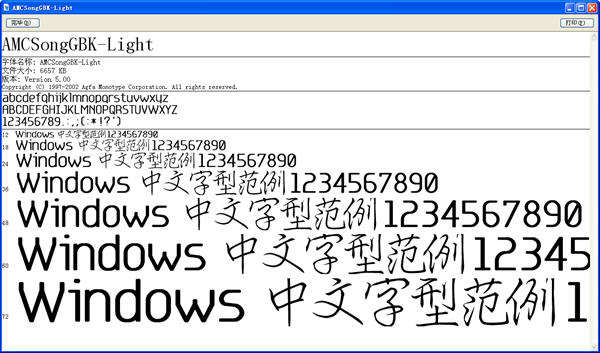
龐中華行書字體是一款非常好用的行書字體,小編為大家?guī)?lái)的是ttf版本,安裝即可使用,字體非常之硬朗,同時(shí)字體沒有那么工整,又帶著一絲活潑的味道,歡迎喜愛的朋友到綠色資源網(wǎng)下載體驗(yàn)!
龐中華,重慶市人,祖籍四川達(dá)州。著名書法家、教育家和詩(shī)人。當(dāng)代中國(guó)硬筆書法事業(yè)的奠基人?,F(xiàn)任文化部中國(guó)硬筆書法協(xié)會(huì)主席,龐中華書法藝術(shù)中心院長(zhǎng)以及國(guó)內(nèi)外一百多所大學(xué)、院校及文化團(tuán)體的顧問、名譽(yù)教授、名譽(yù)校長(zhǎng)等職務(wù)。除書法外,還長(zhǎng)于詩(shī)歌、散文、音樂、演講等藝術(shù)。自一九八零年以來(lái),有三百多種字帖和專著出版發(fā)行,其圖書總印數(shù)累計(jì)達(dá)一億三千萬(wàn)冊(cè)。 中央電視臺(tái)、中國(guó)教育電視臺(tái)多次邀請(qǐng)他主辦;硬筆書法講座;系列節(jié)目,受眾數(shù)以億計(jì)。海內(nèi)外數(shù)家報(bào)刊、電視臺(tái)、電臺(tái)熱情介紹了龐中華的書法藝術(shù)活動(dòng),推動(dòng)7國(guó)內(nèi)外硬筆書法的熱潮。他創(chuàng)辦的龐中華硬筆書法中心及學(xué)院,迄今已培養(yǎng)學(xué)員一百八十余萬(wàn)人。龐氏硬筆書法,清新秀逸,自成一家,被稱為;龐體;。二十多年來(lái),龐中華在國(guó)內(nèi)及港臺(tái)地區(qū)、歐洲、日本、東南亞的高等學(xué)府、中小學(xué)校、機(jī)關(guān)、部隊(duì)演講逾千場(chǎng),反響熱烈,影響了一代又一代中國(guó)人的書法情緣。被海內(nèi)外媒體譽(yù)為;中國(guó)硬筆書法第一人;。
龐中華行書字體是由龐中華所設(shè)計(jì)的行書字體,許多朋友都喜歡這位著名的書法家的字,我們也是在這里將該字體的下載地址推薦給您。